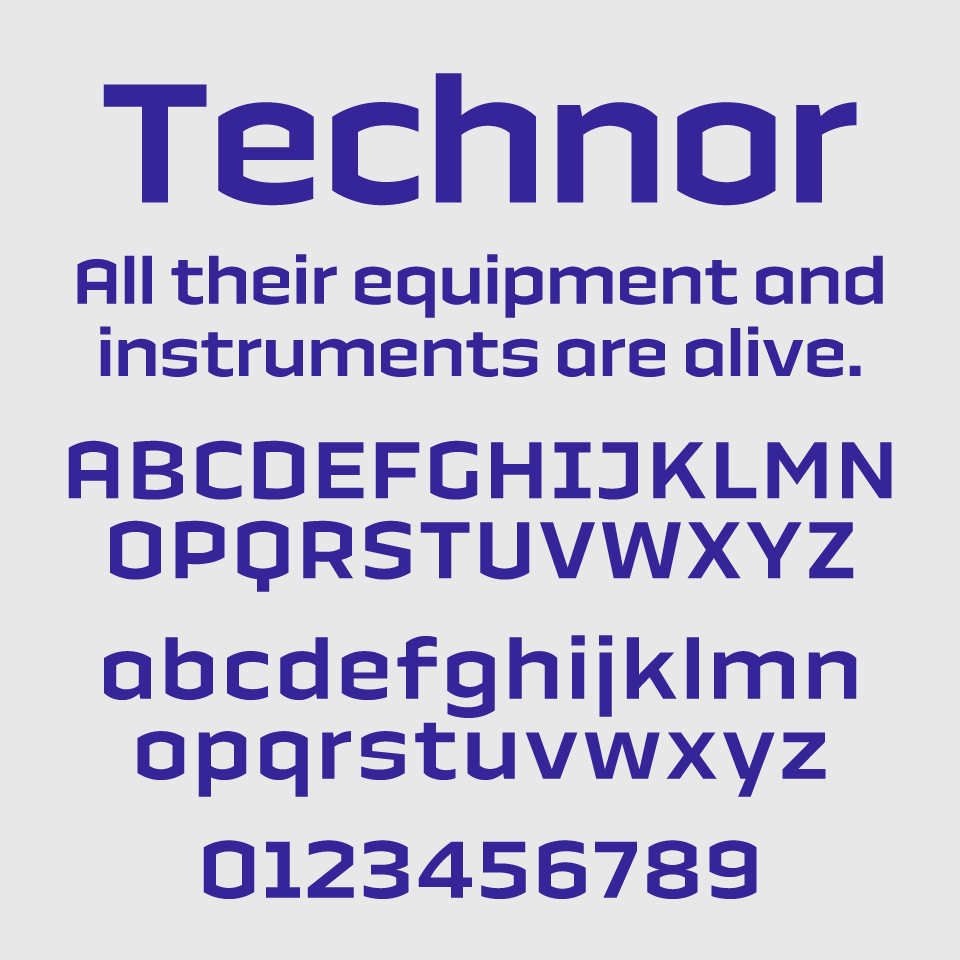
Technorフォントは、ユニークに角張った輪郭と適度な丸みを帯びたカウンター(文字の空白)が特徴のサンセリフフォントです。
直線的でフォルムの中に、ちょっと面白く直線的にトリミングされたようなデザインが素敵なフォントです。SF的なカッコよさがあり、テクノロジー感のある近未来な世界観にもフィットします。